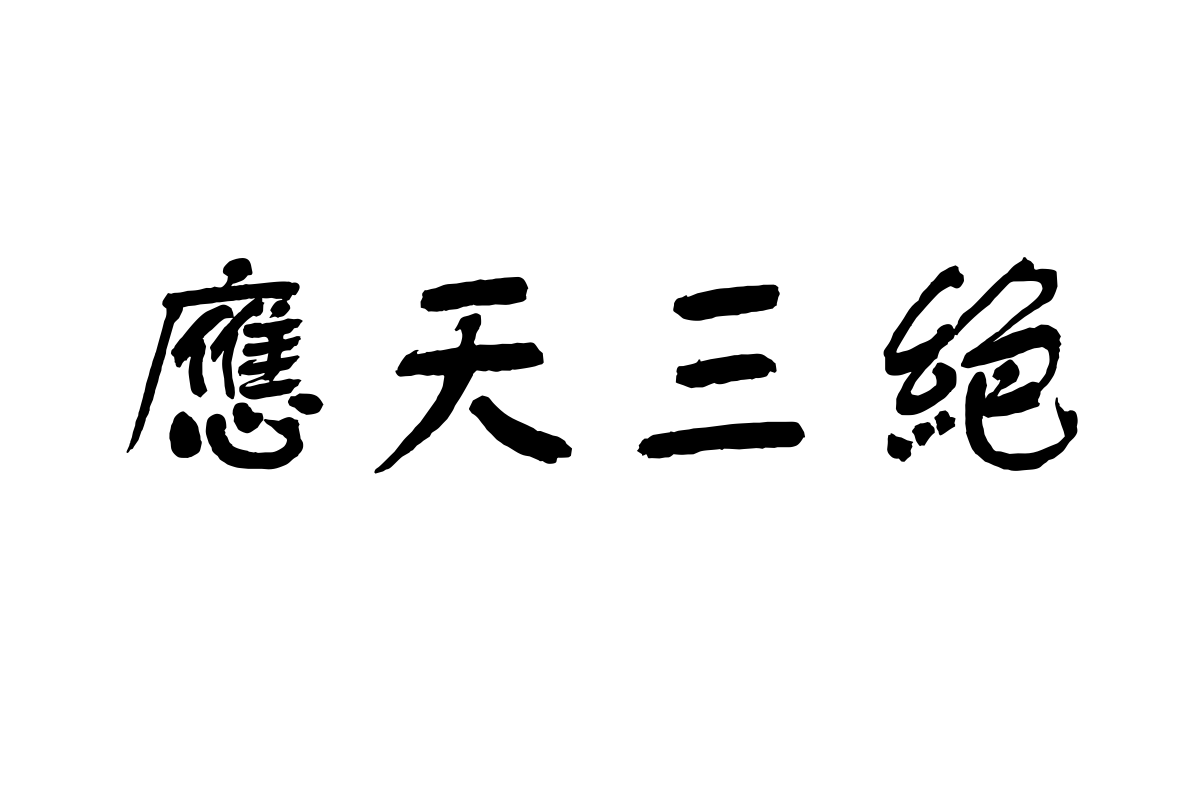
汉仪舒同体繁是一款具有独特设计风格的中文字体,由汉仪公司设计。这款字体以其独特的笔画结构和优雅的线条流畅度而受到广泛欢迎。它适用于各种印刷品和数字媒体,如书籍、杂志、报纸、广告、网站等。汉仪舒同体繁的特点是字形圆润饱满,线条流畅自然,给人一种舒适的感觉。同时,这款字体也具有较高的辨识度和可读性,适合用于需要清晰易读的场合。